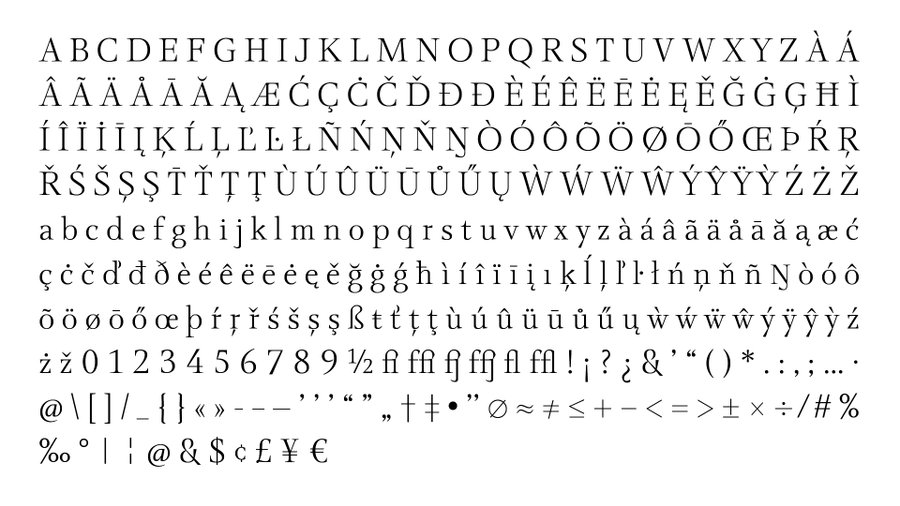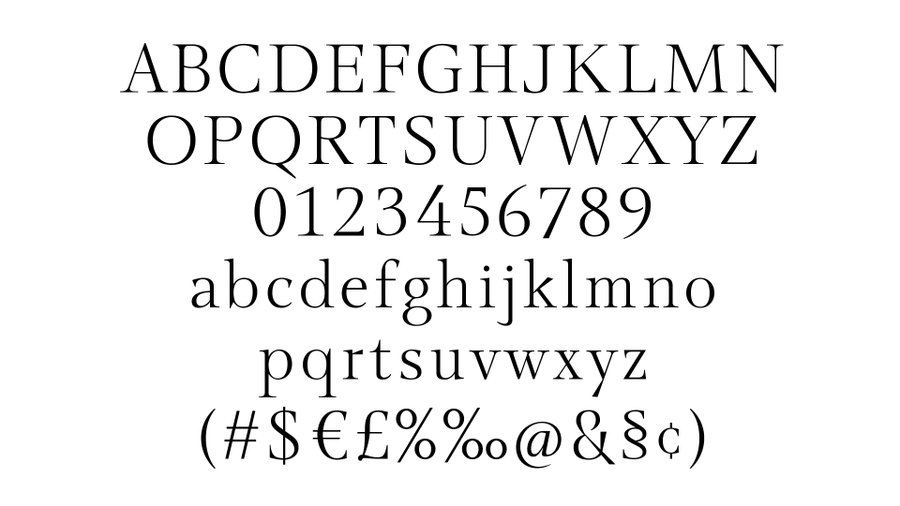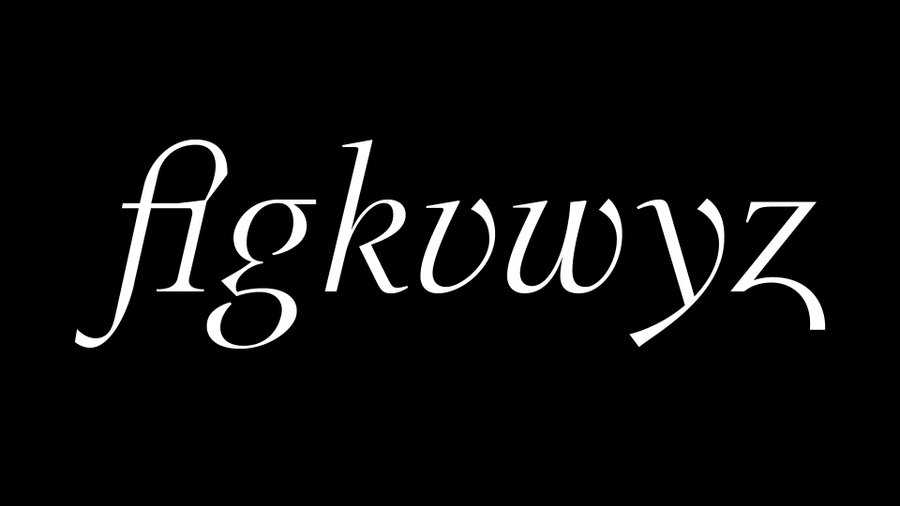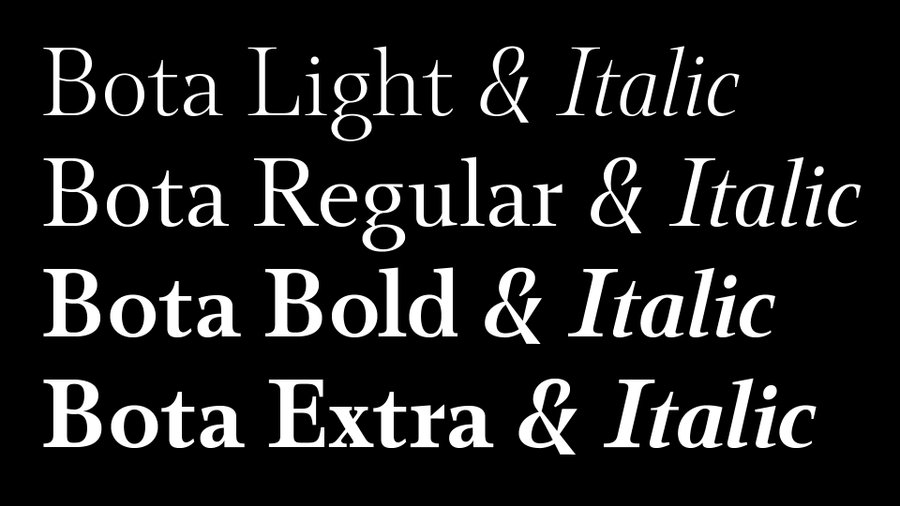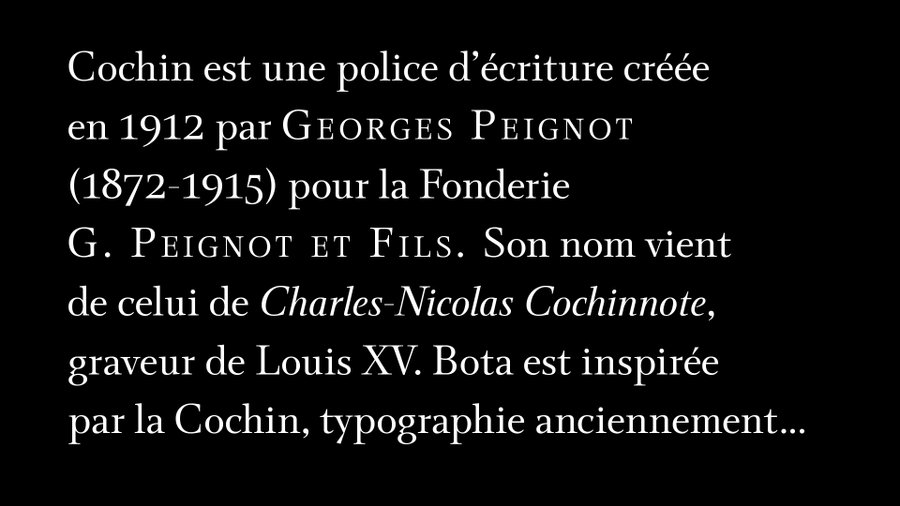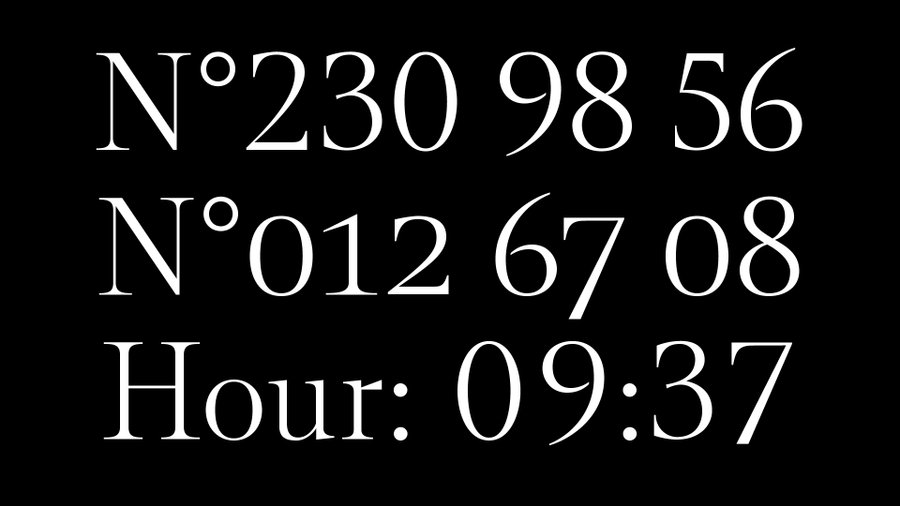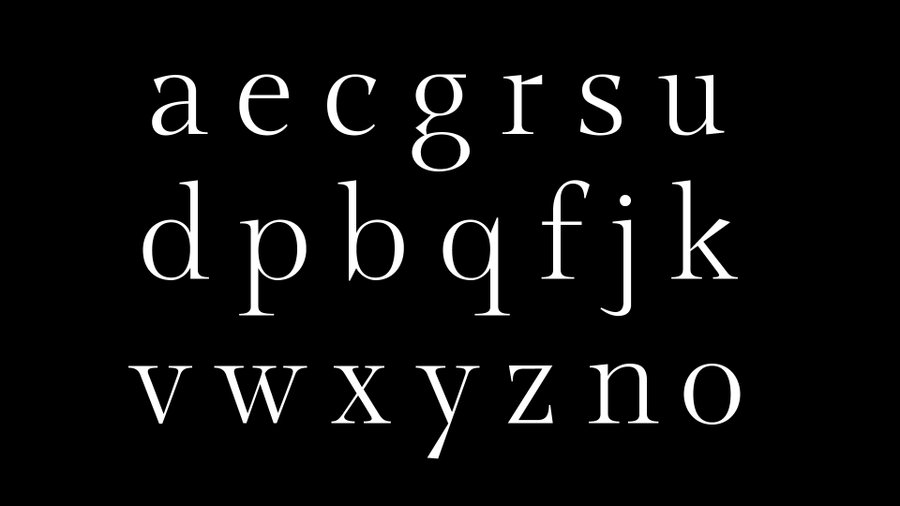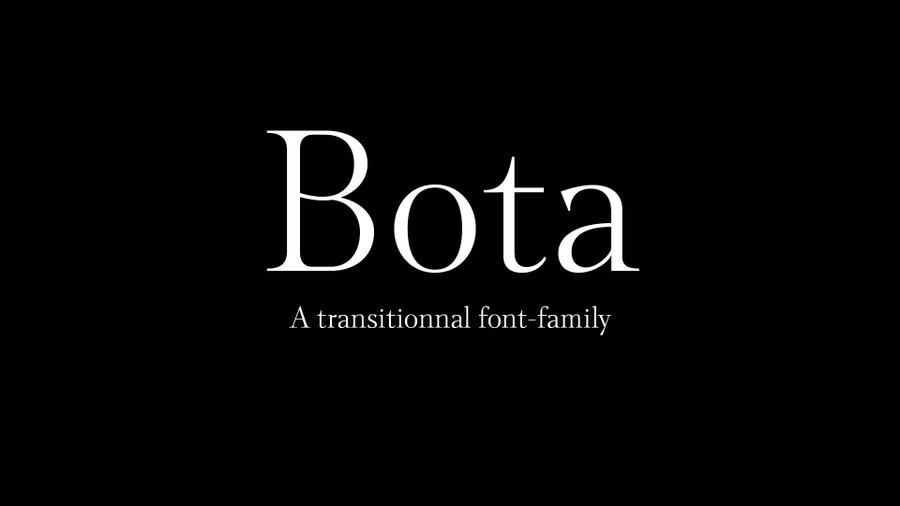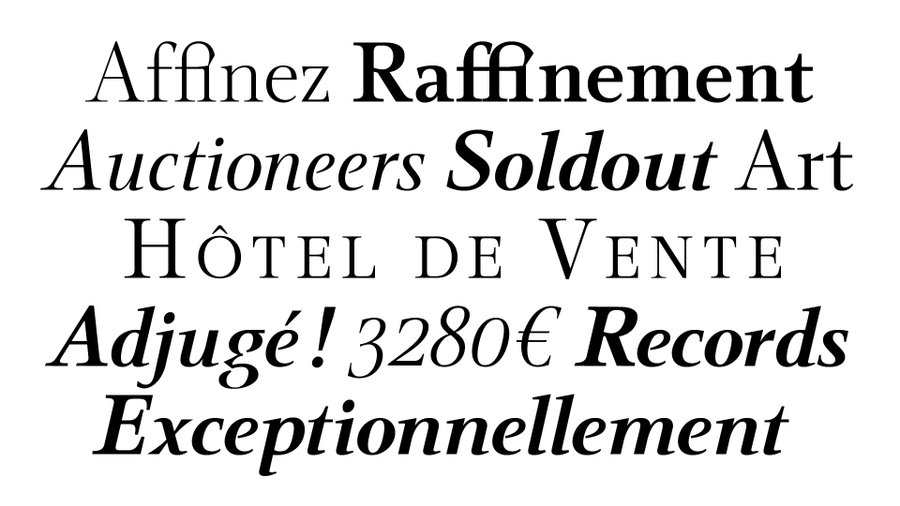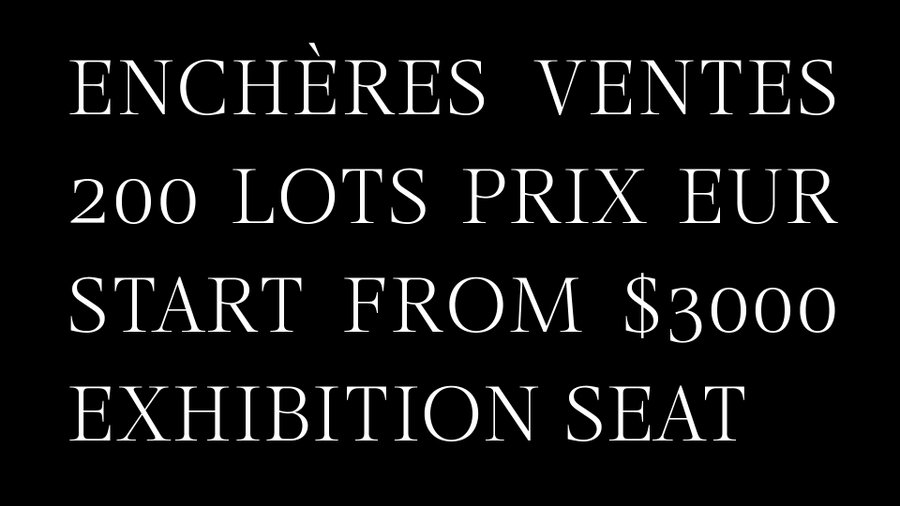
Bota, une typographie sur mesure
Bota est une famille typographique de style transitionnelle.
Dessinée pour l'Hôtel des Ventes de Poitiers. Elle accompagne leur identité visuelle créer simultanément.
La Bota propose 4 graisses et italiques correspondants.